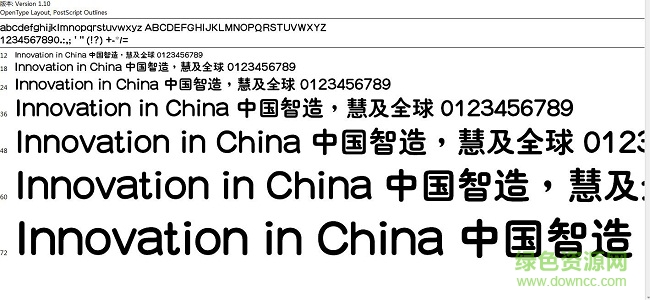
cyuengb(semibold/xbold/light)字體包
cyuengb 什么字體?cyuengb字體是一套優(yōu)質(zhì)的蒙納字體,包含了cyuengb semibold、cyuengb xbold、cyuengb light共3款字體,又園又黑,十分漂亮,喜歡的朋友快來(lái)下載吧!
cyuengb semibold